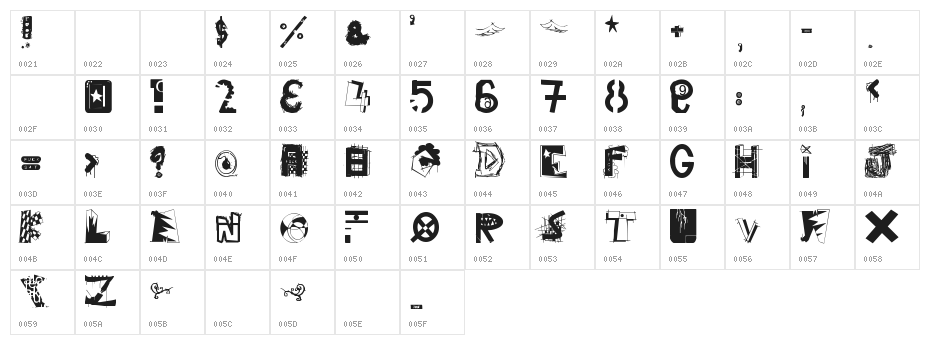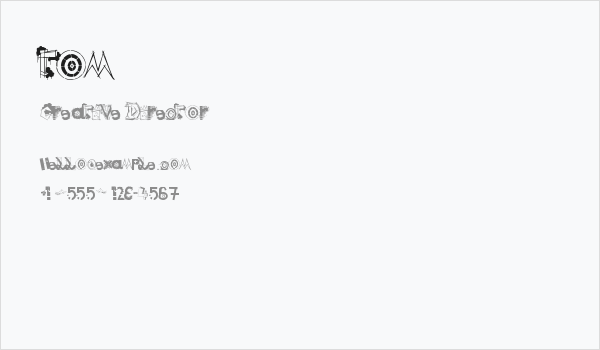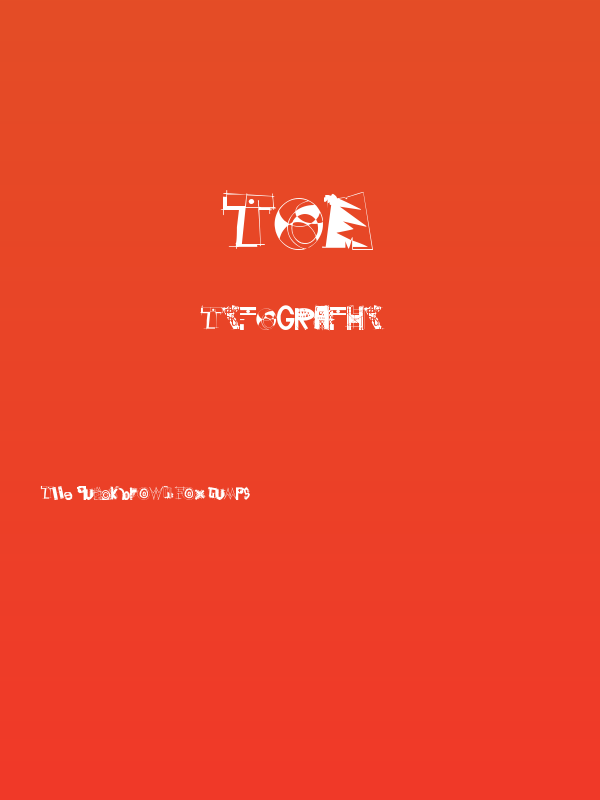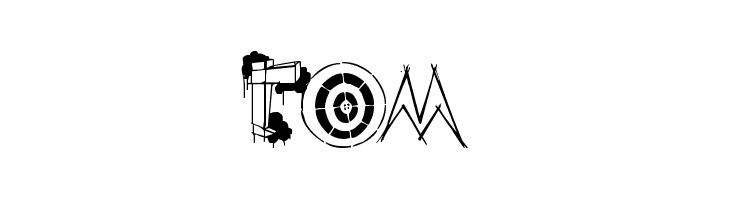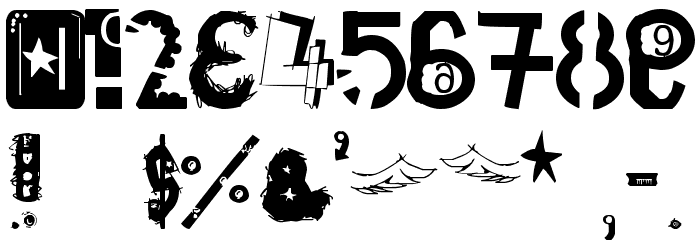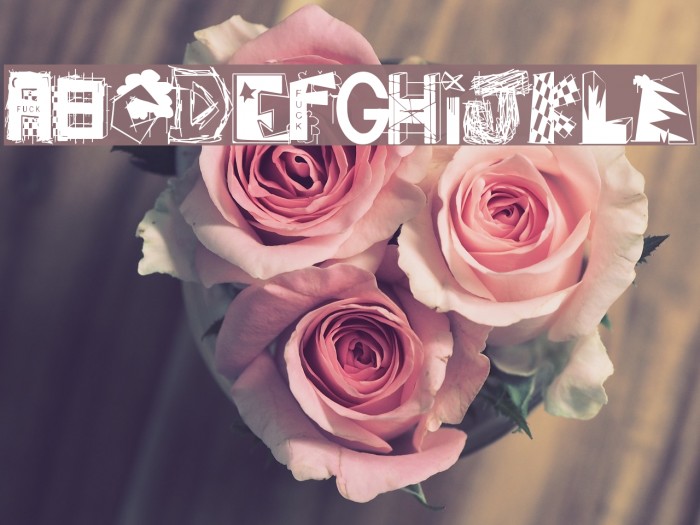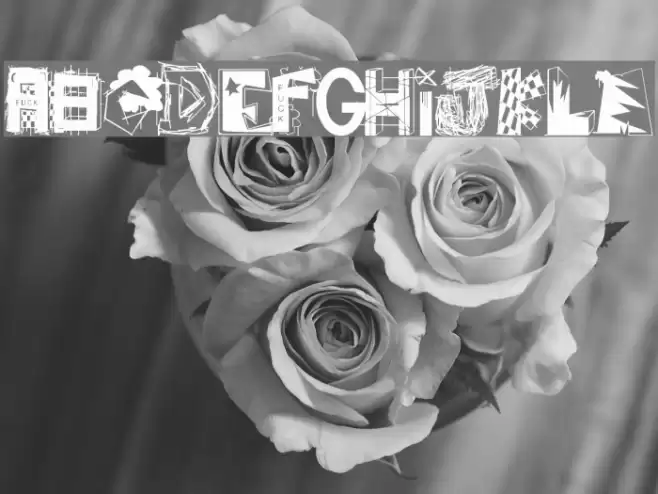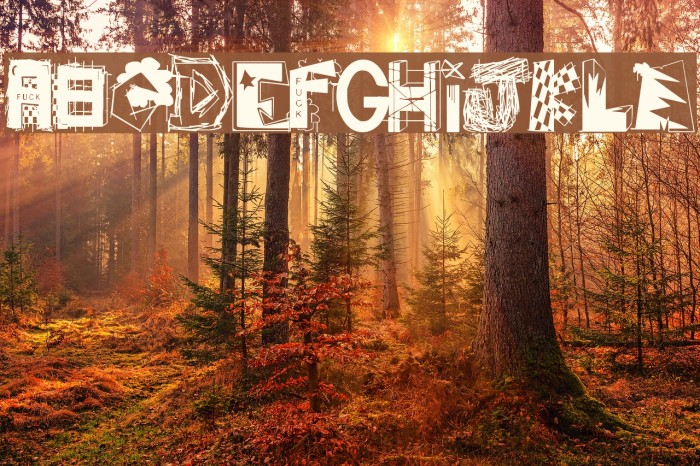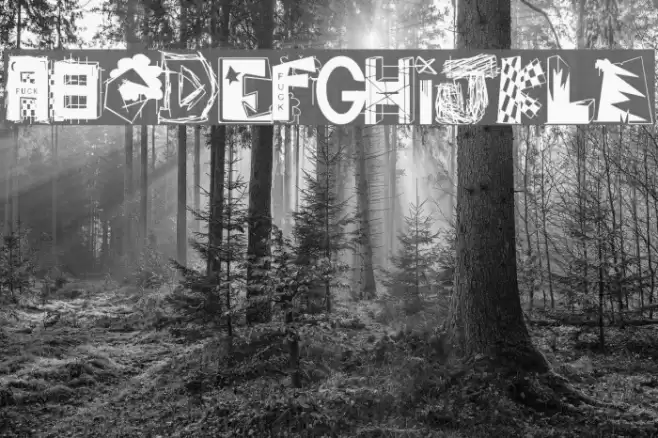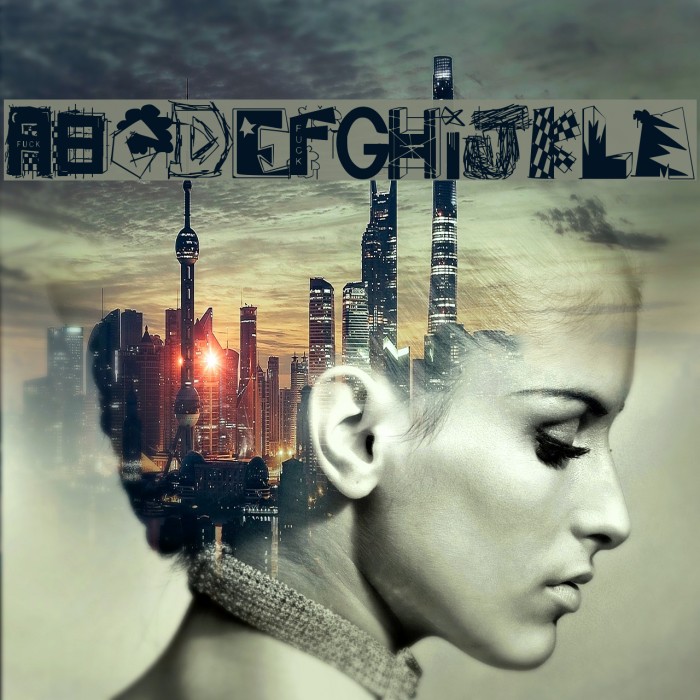
tom Font
| النمط العام | Modern, Artistic, Graffiti |
| مشاريع مقترحة | Ideal for album covers, posters, street art-inspired designs, and creative branding projects. |